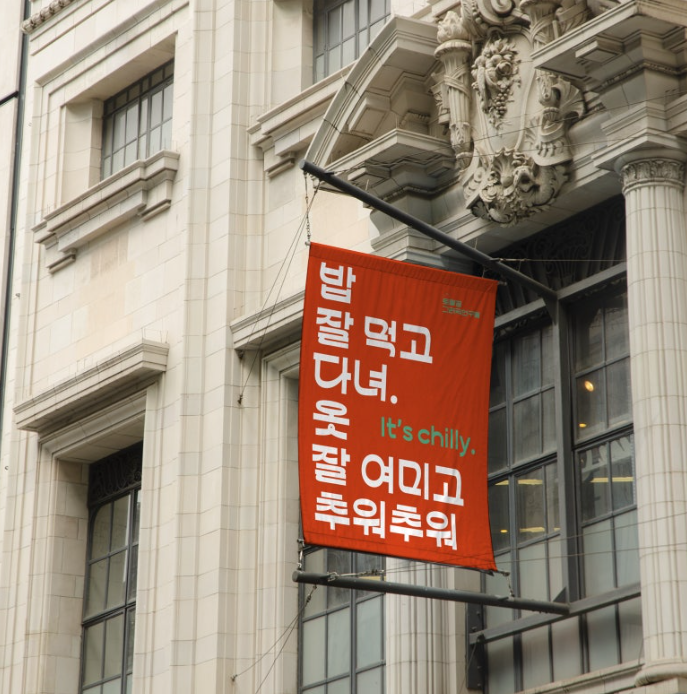
HS잔다리체 무료폰트
HS잔다리체 — 토끼네활자공장에서 배포하는 무료 폰트입니다. 서울 서교동 일대의 옛 지명에서 이름을 얻은, 상경기 시리즈의 개성 있는 제목용 서체
토끼네활자공장이 2025년 10월에 낸 산세리프 서체로, 제작자가 새로 시작한 서울 시리즈의 첫 작품입니다. 제작자는 서울로 이사하며 겪은 장소의 변화와 그때 느낀 감정을 다루는 자전적인 상경기 시리즈라고 밝히고 있습니다.
이름은 서울 마포구 서교동 일대의 옛 지명에서 왔습니다. 잔다리는 자잘한 다리라는 뜻으로, 조선시대에 이 일대에서 한강을 건너려면 지나야 했던 작은 다리들을 가리키던 순우리말입니다. 한자로 옮기면 세교가 되고 동쪽 잔다리가 동교동, 서쪽 잔다리가 서교동이 됐습니다. 제작자는 잔다리 일대를 조용히 산책하며 느낀 공감각적 심상을 서체에 담았다고 적었습니다. 유연한 곡선, 귀여운 듯 단단하고 날카로워 보이는 듯 포근한 형태라는 것입니다.
만든 방식이 특이합니다. 제작자는 이 서체가 90% 이상 인공지능 자동화로 개발됐으며 사람이 할 일은 자음과 모음 한 세트를 디자인하는 것뿐이었다고 밝혔습니다. 파이썬으로 글자를 하나의 모듈로 치환해, 자모가 거푸집에 금속을 붓듯 스스로 크기를 바꾸도록 만들었다는 설명입니다. 굵기는 하나이고 한글은 2,748자입니다. 쓰기 전에 확인할 것이 하나 있습니다. 인쇄와 웹, 영상에는 자유롭게 쓸 수 있지만 로고나 브랜드 아이덴티티로 쓰려면 별도의 라이선스 비용이 듭니다.